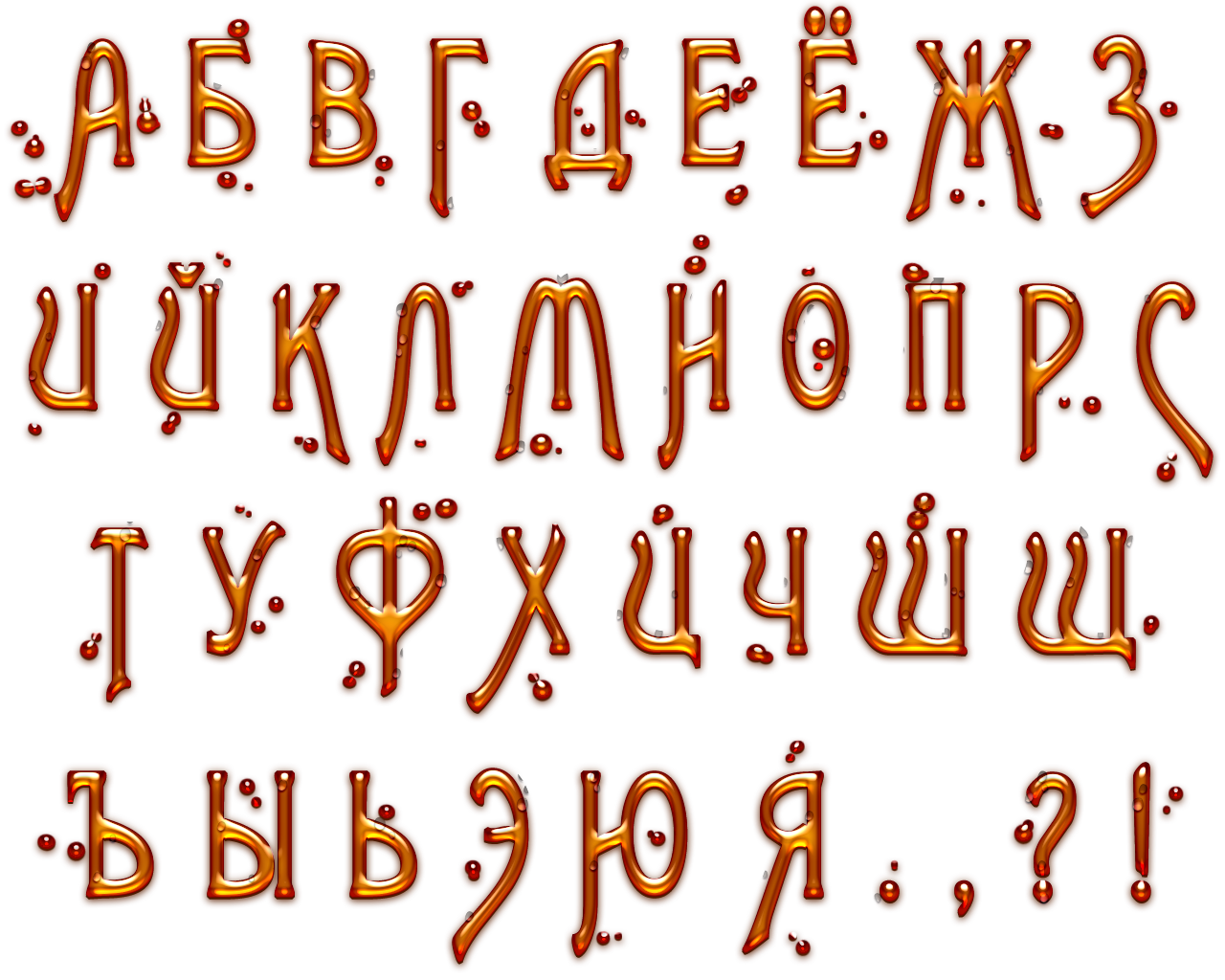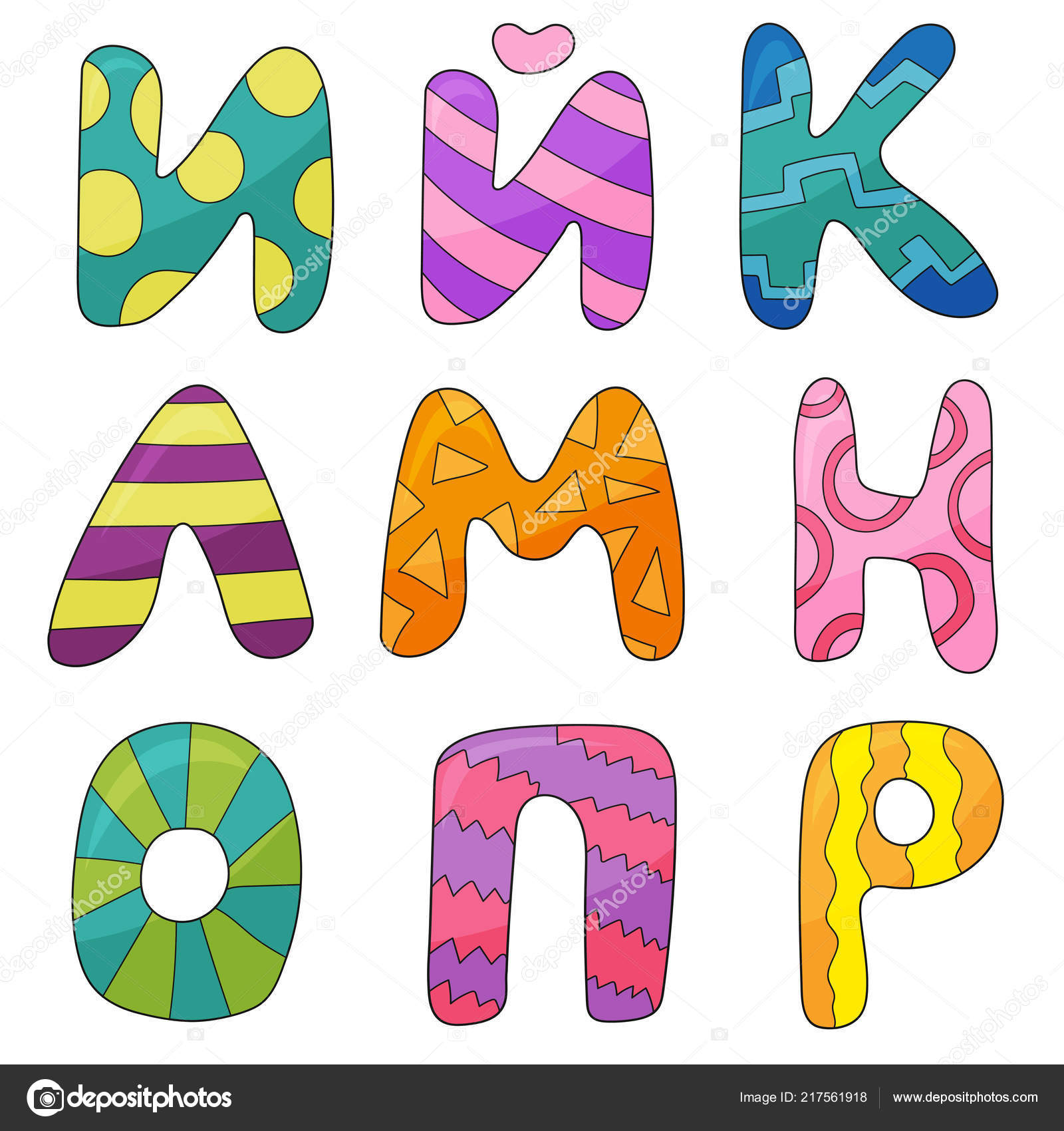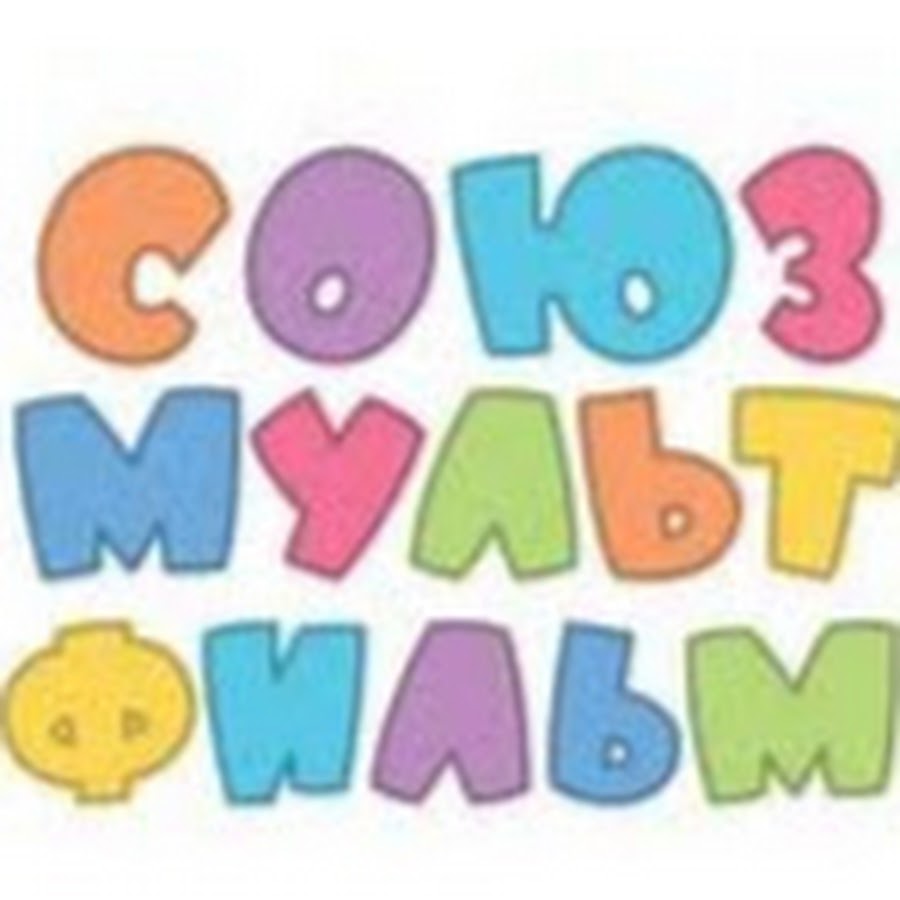
Веселые мультяшные шрифты в количестве 15 штук
Здравствуйте, дорогие друзья. Давненько я не выкладывал шрифты, которые пользовались большой популярностью у меня сайте. И тут столкнулся с поиском мультяшного шрифта для одного лого и решил сделать сборку из 15-и веселых мультяшных кириллических шрифтов. Некоторые шрифты из этой сборки встречаются в предыдущих моих постах, но я все равно выложил, чтобы было из чего выбрать. Тут есть шрифт из Disney, Ледникового периода, Незнайки на Луне. Каждый шрифт вы сможете скачать отдельно прямо с моего сервера без помощи каких-либо файлообменников и, самое главное, совершенно бесплатно. Поехали:
Рисованный мультяшный кириллический шрифт
Классный веселый русский шрифт
Кириллический шрифт Disney
Жирный кириллический шрифт из мультика
Стильный рисованный мультяшный шрифт
Веселый жирный шрифт для титров мультика
Контурный мультяшный русский шрифт
Классный веселый кириллический шрифт
Контурный моноширинный мультяшный шрифт
Моноширинный мультяшный кириллический шрифт
Шрифт для титров в мультике
«Безалаберный» мультяшный кириллический шрифт
Русский шрифт из «Незнайка на луне»
Строгий, но веселый шрифт в кириллической раскладке
Тонкий мультяшный шрифт
Вот все 15 кириллических шрифтов из этой сборки, которые можно использовать для титров мультика или веселого фильма, для создания веселого яркого логотипа, баннера на детскую тематику.
Подборка мультяшных кириллических шрифтов для Photoshop
Мультяшные шрифты привлекают своей необычностью, в первую очередь. Это, как правило, пляшущие буквы, жирные или контурные вариации. Но именно такими шрифтами оформляют детские сайты, книги, плакаты, буклеты, открытки и многое другое. Их удобно читать, они подходят для разных объёмов текста и даже для комиксов.
Мы подобрали для вас несколько мультяшных шрифтов с поддержкой кириллицы в разных художественных стилях. Все шрифты собраны в единый архив.
AsA
Шрифт для комиксов. Содержит прописные буквы, легкую небрежность, наклон, разную толщину линий.
Chicken butt
Необычность начертания подходит для видео, мультиков, заголовков.
DisneyPark
Тут и говорить не о чем)) Тот самый шрифт, которым написано DISNEY в начале фильмов и мультфильмов компании.
Dnk
Брутально угловатый, резкий, жирный шрифт. Подходит для комиксов и смотрится гармонично в окружении действий.
Ds brushes
Стильный рисованный шрифт, который напоминает вариации шрифта из некоторых советских мультфильмов, детских книг того периода.
ICE_AGE
Стилизация шрифта из мультфильмов «Ледниковый период».
Foo
Особенно жирный и крупный шрифт, исключительно для заголовков.
IceAge
Еще одна вариация шрифта для Ледникового периода. Но более крупная, полностью окрашенная.
JFRocOut и JFRocSol
Каменные или треснутые шрифты. Подходят для заголовков преимущественно.
KOMIKAX
Характерный шрифт для комиксов, который встречается практически во всех книгах.
Lcblowzy
Контурный, расплывчатый, жирный шрифт. Напоминает надписи на стекле или чем-то жидким на твердой поверхности.
Шрифты для комиксов и мультяшные шрифты
Хочу представить вашему вниманию небольшую подборку, в которую вошли
1. Один из классических шрифтов, которые используют в комиксах. В нем только прописные буквы, легкие небрежность, и наклон, и разная толщина линий. В общем в баллонах чьих-то комиксов вы его наверняка встречали, попробуйте вставить в свои.
2. Если переводить название этого шрифта, получится что-то типа “куриная задница”. Я не знаю почему так. Мне этот шрифт приглянулся необычной формой и полосатостью. Думаю вполне уместен в каких-то мультипликационных заголовках и всяком таком. Имеет как прописные, так и строчные символы.
3. Брутально угловатый, резкий, жирный шрифт. Тоже видал где-то в комиксах. Смотрится четко и гармонично особенно в окружении экшена. Традиционно для комиксовских шрифтов отсутствуют строчные символы.
4. Этот мне напоминает шрифт из старых мультиков, типа “Ну, погоди!”. Ну там когда авторов перечисляют в титрах. Похож очень по-моему. В общем для стенгазет, новых годов и прочих подобных детских тем. Подойдет идеально.
5. Еще один типичный шрифт из комиксов. Во всевозможных человеках пауках, росомахах, марвелах и прочих супергероях вы его обязательно встретите.
6. Сказочно – эксцентричный, так бы я его назвал. Очень понравился этот шрифт. Асимметрия его не мешает чтению, но втыкает большую изюмину в его мякоть. Прекрасно подойдет для оформления каких-нибудь волшебных сказок или заклинаний. Ну или еще для чего-то.